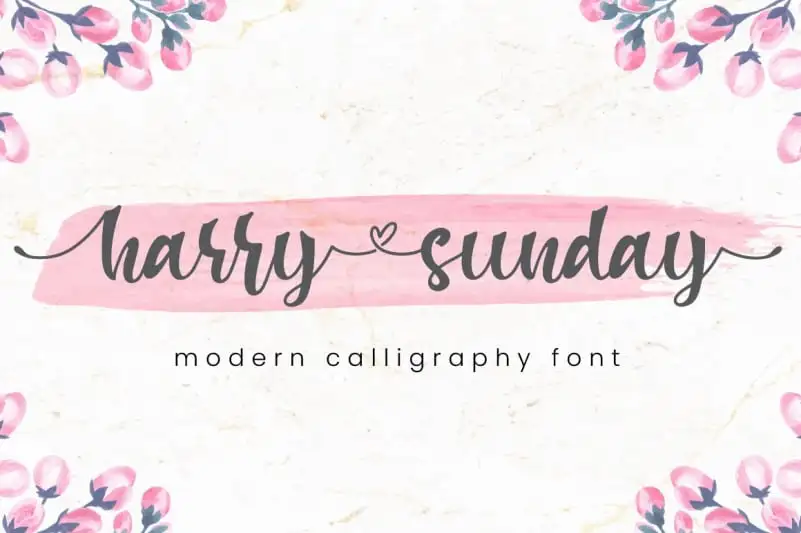
Harry Sunday Calligraphy Font
Harry Sunday Calligraphy Font é uma nova variante do tipo de letra script feito à mão. Este novo adereço chega para completar sua coleção de tipos de fontes script. É um trabalho delicado e surpreendentemente distinto, criado pelo Attype Studio. Esta fonte tem três estilos distintos. Inspirada em escrita a mão, Harry Sunday Calligraphy Font se destaca por seu estilo versátil e peculiarmente detalhado. É perfeita para artistas digitais e designers que procuram um recurso gráfico único e intrigante. Suas curvas arredondadas e linhas suaves criam uma atmosfera romântica e aconchegante, ideal para aplicar em cartazes de eventos, posters ou até mesmo na elaboração de mensagens personalizadas no seu próximo projeto. Adquira Harry Sunday Calligraphy Font e invista em sua estilização única. Use esta fonte para criar designs impecáveis que destacam sua habilidade criativa em projetos digitais. Fique ligado para mais tipos de fontes de alta qualidade!